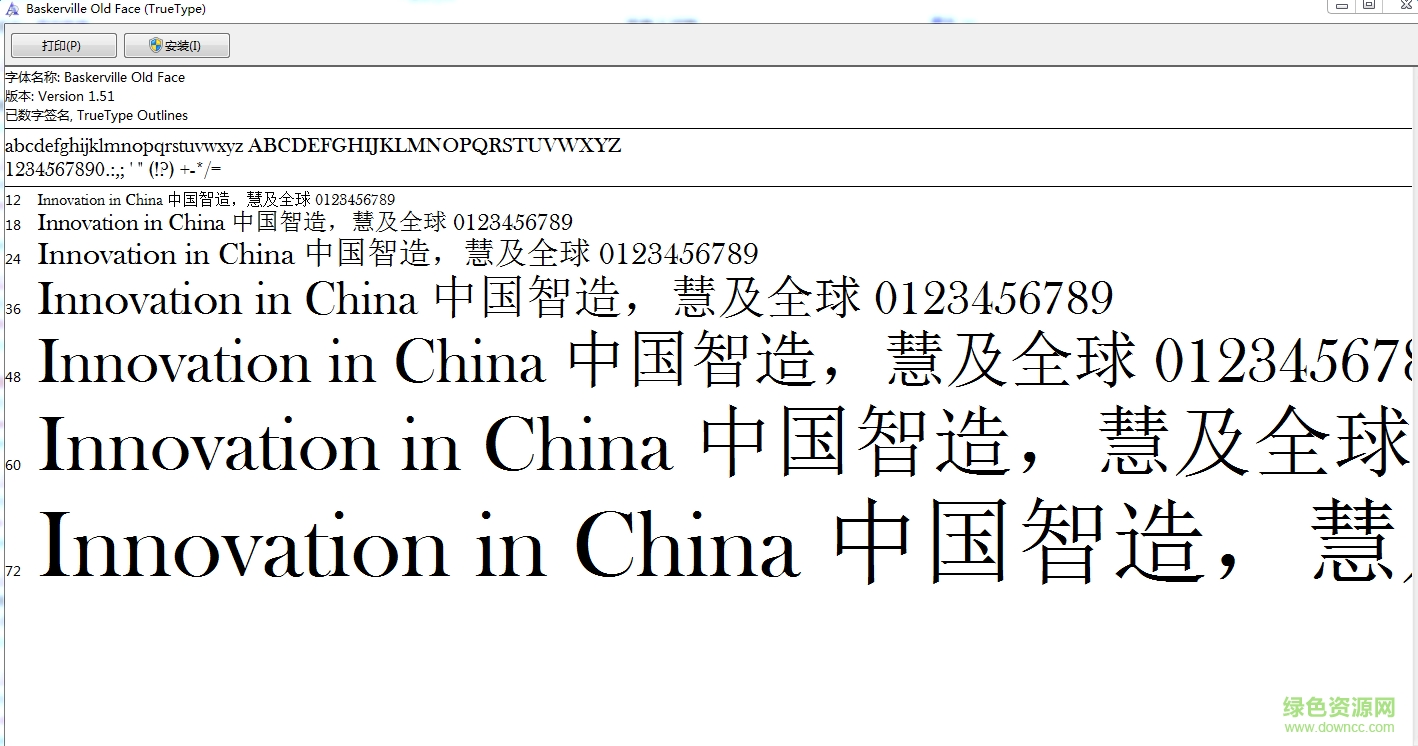
baskerville old face
baskerville old face字體是一款溫和美觀的英文字體,筆畫粗細變化得宜,線條流暢,結(jié)構(gòu)規(guī)范,應(yīng)用廣泛,需要的朋友快來綠色資源網(wǎng)下載吧!
baskerville old face字體的襯線的特征非常明顯,字體效果出色,適合做各類書刊、雜志、文章的正文字體!